Am 16. März 2019 ist Axel Bertram, bekannter Gebrauchsgrafiker der DDR, kurz vor seinem 83. Geburtstag nach langer schwerer Krankheit in Berlin gestorben. Seinen Namen kannten nur Spezialisten, seine Werke kennt jeder, der in der DDR gelebt hat. Geboren in Dresden und aufgewachsen in Freital, arbeitete Bertram nach dem Studium an der Kunsthochschule in Berlin-Weißensee seit 1960 als freiberuflicher Grafiker. Von 1977 bis 1992 unterrichtete er zugleich als Professor für Schrift und gebrauchsgrafisches Gestalten an der Berliner Kunsthochschule.
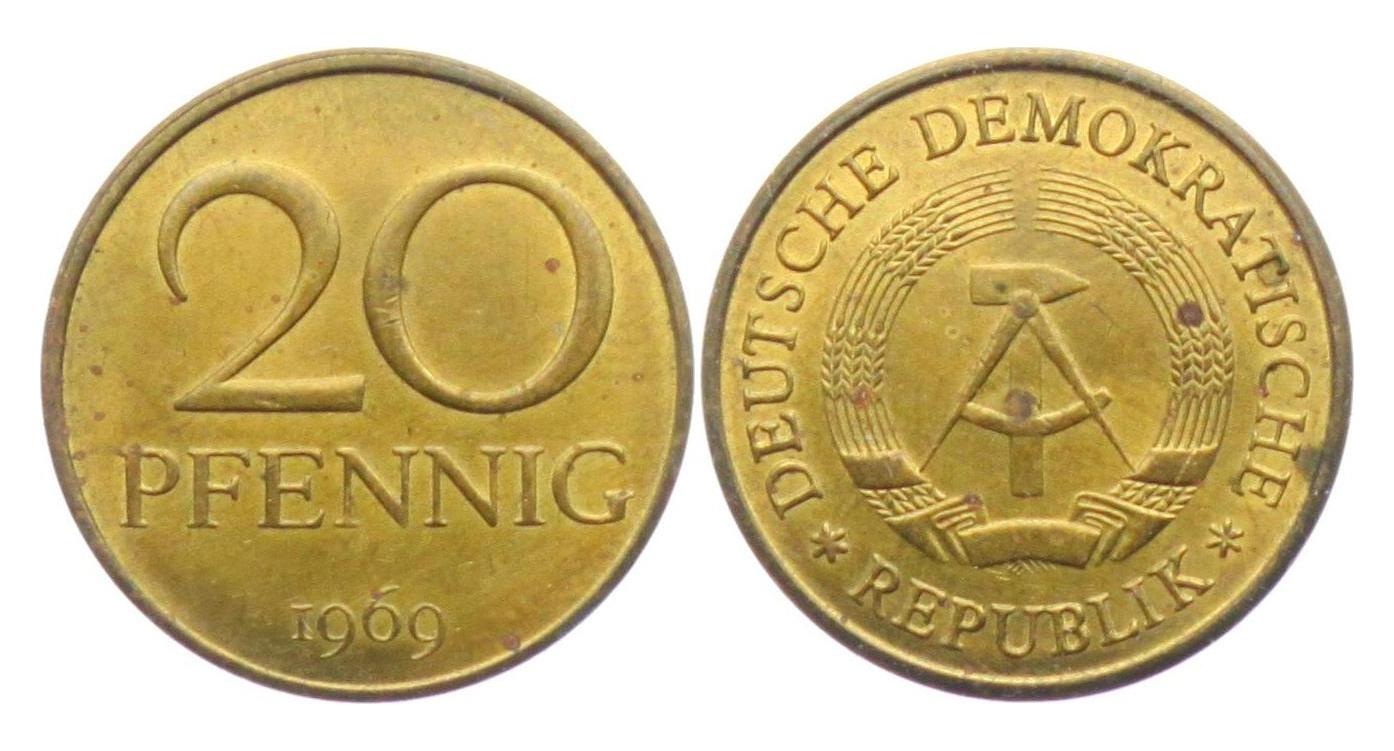
Bertram war auf sämtlichen Feldern des grafischen Designs tätig. Er gestaltete zahlreiche Bücher und Plakate und entwarf das Layout der Zeitschriften »Sibylle« und »Wochenpost«. Er gestaltete er Umlauf- und Gedenkmünzen, so das 20-Pfennig-Stück und die 5-Mark-Umlaufmünze der DDR. Auch zahlreiche Briefmarken gehen auf ihn zurück.
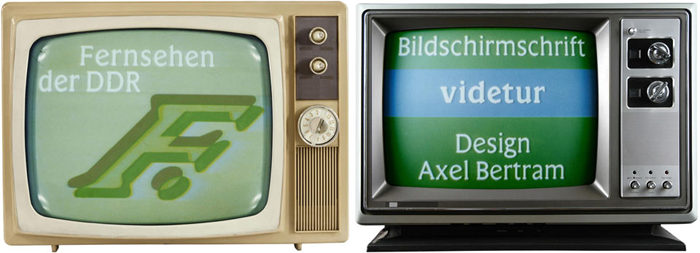
Als Schriftgestalter entwickelte er die spezielle Fernsehschrift Videtur sowie den OpenType-Font Rabenau Pro. Bertram legte keinen Wert auf eine unverwechselbare Handschrift. Er sah sich vielmehr als Diener des Lesers, Betrachters oder Nutzers und suchte stets aufs Neue nach der perfekten Lösung einer konkreten Aufgabe. Mit einem an der Tradition geschulten Formbewußtsein und dem Selbstverständnis eines Künstlers, der nicht für das Museum, sondern für den Alltag arbeitet, nahm er mehr als fünf Jahrzehnte lang jede Gelegenheit wahr, Neues auszuprobieren. Einen Gesamtüberblick über sein Werk bietet der Band: Axel Bertram. Grafisches Gestalten in fünf Jahrzehnten. Lehmstedt Verlag, Leipzig.